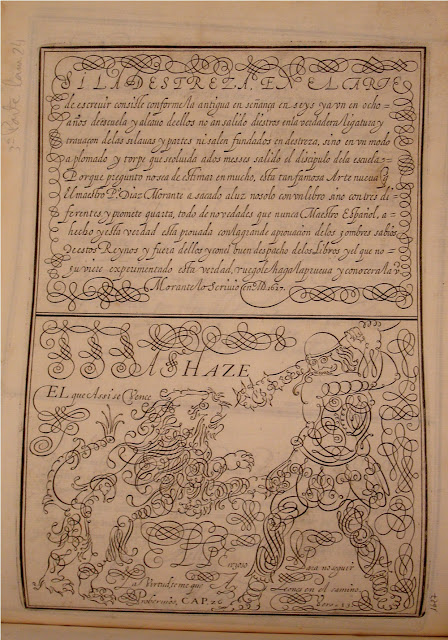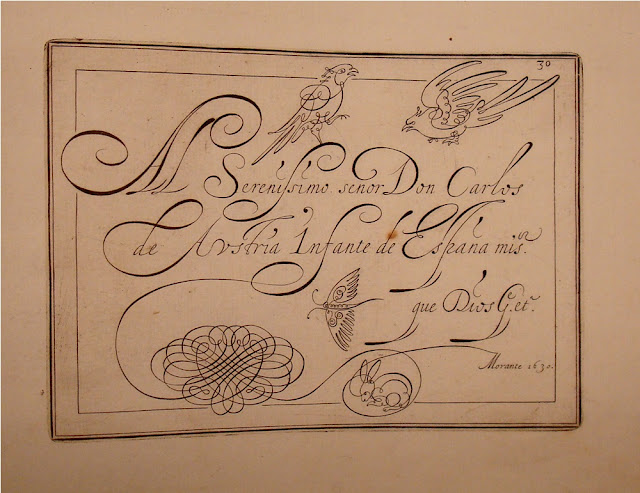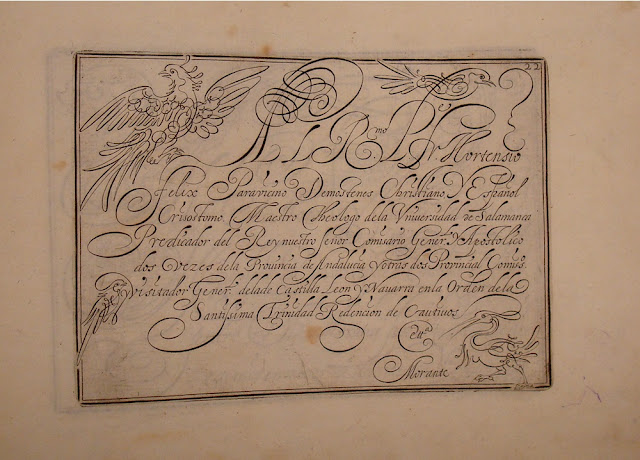
En la España del s. XVII, destacaron algunas familias de calígrafos como los Moya, los Zabala o los Morante, todos ellos con un alto grado de virtuosismo en sus muestras y una excepcional habilidad pendolista. La moda de la época desarrolló al máximo un barroquismo en las formas y también una imaginación sin límites en la decoración caligráfica, incluyendo dibujos de personajes mitológicos, animales, formas decorativas y orlas etc
La familia de los Morante formada por padre e hijo y llamados los dos Pedro, fueron los mas conocidos por el hecho de haber publicado sus obras y por el gran éxito de sus muestras.
Dentro de la historia de la Caligrafía estas ediciones son de extraordinaria rareza y de difícil descripción bibliográfica a causa de los pocos ejemplares que existen y la variedad de diferencias que existen entre ellas, diríase que no hay dos iguales.
Se cree que Pedro Morante nació en Alcázar de San Juan, mas o menos en 1566 y murió el 1636 en Madrid. Según explica Cotarelo (1) de orgulloso carácter al que le gusta hablar de sus méritos y le duele no ser reconocido por sus semejantes. Morante decide tallar el mismo sus muestras caligráficas al no poder encontrar un buen grabador para reproducirlas y asume el mismo el coste de sus ediciones, esto sin duda le ocasionó muchos y costosos gastos. Su intención inicial era la de publicar cinco partes de su "Arte de escribir", pero la quinta entrega no pudo costearla y no vio la luz editorial.
La familia de los Morante formada por padre e hijo y llamados los dos Pedro, fueron los mas conocidos por el hecho de haber publicado sus obras y por el gran éxito de sus muestras.
Dentro de la historia de la Caligrafía estas ediciones son de extraordinaria rareza y de difícil descripción bibliográfica a causa de los pocos ejemplares que existen y la variedad de diferencias que existen entre ellas, diríase que no hay dos iguales.
MORANTE Y SUS EDICIONES
Se cree que Pedro Morante nació en Alcázar de San Juan, mas o menos en 1566 y murió el 1636 en Madrid. Según explica Cotarelo (1) de orgulloso carácter al que le gusta hablar de sus méritos y le duele no ser reconocido por sus semejantes. Morante decide tallar el mismo sus muestras caligráficas al no poder encontrar un buen grabador para reproducirlas y asume el mismo el coste de sus ediciones, esto sin duda le ocasionó muchos y costosos gastos. Su intención inicial era la de publicar cinco partes de su "Arte de escribir", pero la quinta entrega no pudo costearla y no vio la luz editorial.
1- DÍAZ MORANTE, PEDRO
"NUEVA ARTE, DONDE SE DESENTIERRAN LAS IGNORANCIAS QUE HASTA OY HA AVIDO EN ENSEÑAR A ESCRIVIR. Compuesto por el Maestro Pedro díaz Morante..."Madrid: Luys Sanchez impressor del Rey nuestro señor. Año MDCXVI
- 2ª Portada caligráfica: “NUEVA ARTE DE ESCRIBIR INVENTADA CON EL FABOR DE DIOS POR EL MAESTRO PEDRO DÍAZ MORANTE... “ Con fecha 1615.
Folio apaisado, 5 hs prels. 21 foliadas y 17 o 18 láminas (al final repite las señas de la impresión.)
De los pocos ejemplares que se conservan solo uno conserva el texto de las 21 folios de explicaciones (ejemplar según Cotarelo (1) de la Biblioteca de la Escuela Normal de Maestros y actualmente en el Victoria & Albert Museum de Londres) en la descripción de Cotarelo (1) dice que en las posteriores ediciones se mejora y amplia con mejores ejemplos el texto.
De esta primera parte del libro de Morante se conservan localizados según A Martínez Pereira (2), pág 227, solo tres ejemplares:
Madrid, CSIC M-Residencia de Estudiantes: R-531 ( Ex Rico y Sinobas)
Londres, Victoria & Albert Museum: 86.K.41-50 (Obra completa en 10 volúmenes)
Nueva York. Hispanic Society ( Ex- Félix Boix)
El ejemplar que podemos describir en Bibliotypes solo conserva 16 láminas de las 18? entre las cuales hay la portada caligráfica: Os reproduzco unas cuantas de ellas:
"NUEVA ARTE, DONDE SE DESENTIERRAN LAS IGNORANCIAS QUE HASTA OY HA AVIDO EN ENSEÑAR A ESCRIVIR. Compuesto por el Maestro Pedro díaz Morante..."Madrid: Luys Sanchez impressor del Rey nuestro señor. Año MDCXVI
- 2ª Portada caligráfica: “NUEVA ARTE DE ESCRIBIR INVENTADA CON EL FABOR DE DIOS POR EL MAESTRO PEDRO DÍAZ MORANTE... “ Con fecha 1615.
Folio apaisado, 5 hs prels. 21 foliadas y 17 o 18 láminas (al final repite las señas de la impresión.)
De los pocos ejemplares que se conservan solo uno conserva el texto de las 21 folios de explicaciones (ejemplar según Cotarelo (1) de la Biblioteca de la Escuela Normal de Maestros y actualmente en el Victoria & Albert Museum de Londres) en la descripción de Cotarelo (1) dice que en las posteriores ediciones se mejora y amplia con mejores ejemplos el texto.
De esta primera parte del libro de Morante se conservan localizados según A Martínez Pereira (2), pág 227, solo tres ejemplares:
Madrid, CSIC M-Residencia de Estudiantes: R-531 ( Ex Rico y Sinobas)
Londres, Victoria & Albert Museum: 86.K.41-50 (Obra completa en 10 volúmenes)
Nueva York. Hispanic Society ( Ex- Félix Boix)
El ejemplar que podemos describir en Bibliotypes solo conserva 16 láminas de las 18? entre las cuales hay la portada caligráfica: Os reproduzco unas cuantas de ellas: